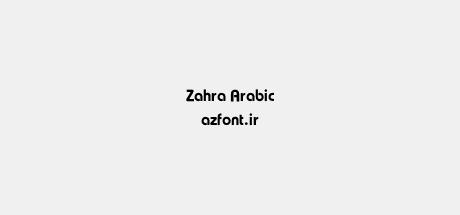
Zahra Arabic
فونت زیبای رایگان Zahra Arabic
قلم زیبای Zahra Arabic Bold از سری قلم های بسیار زیبا برای تایپوگرافی و لوگو تایپ می باشد.این قلم در وزن Bold و توسط Yousef bkw Circle mhairy 2011 طراحی و منتشر شده است.